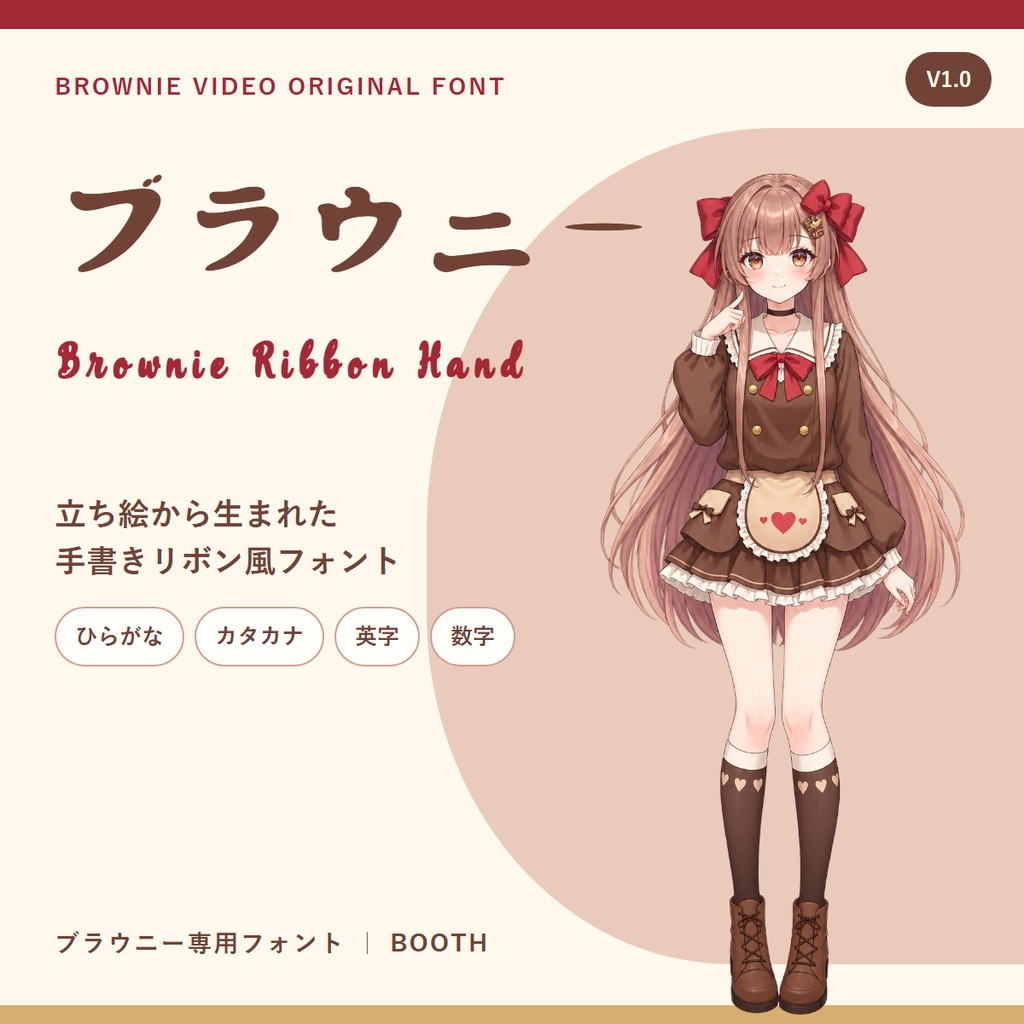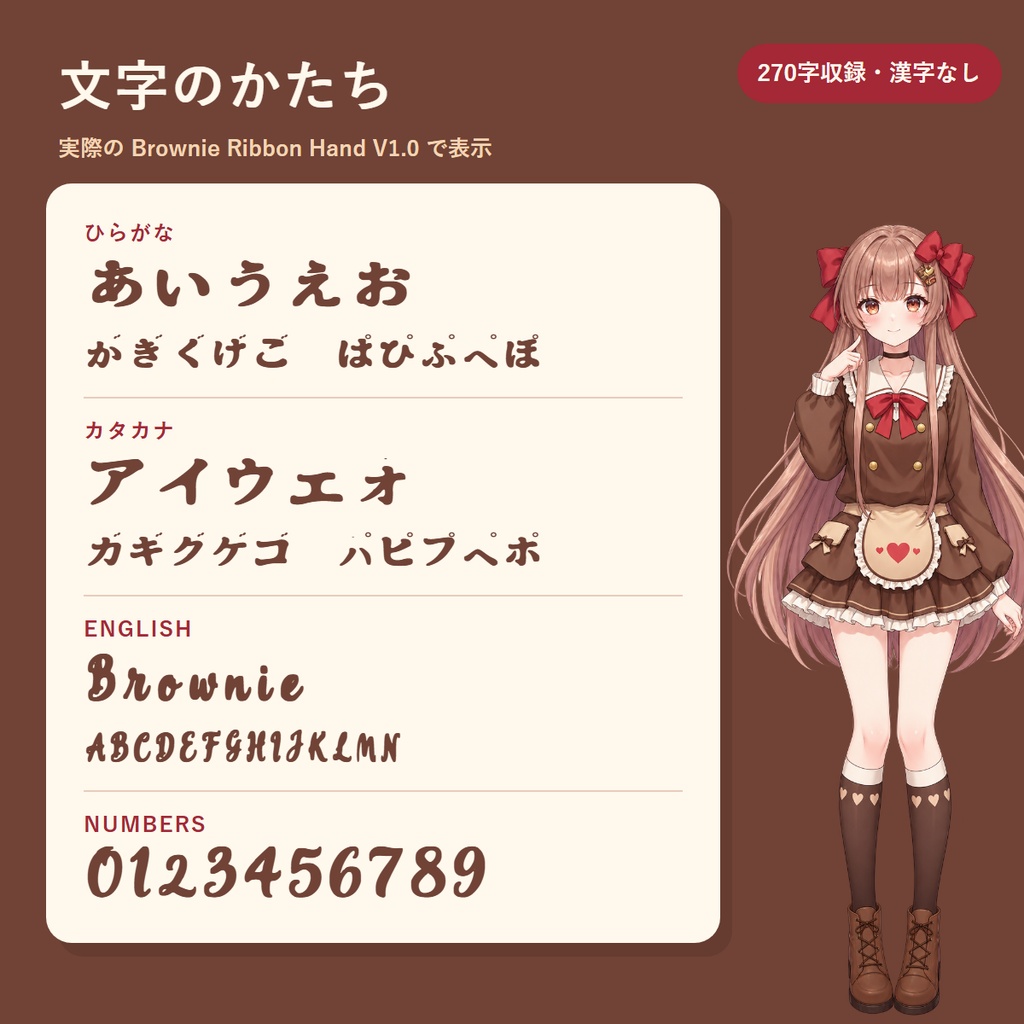
ブラウニーのイメージしたフォント
【商品紹介】 TITAN学園として登場するブラウニーの立ち絵にあるリボンと衣装の雰囲気をもとに制作した、手書き風のタイトル用フォント「Brownie Ribbon Hand V1.0」です。動画のタイトル、サムネイル、配信画面、ロゴ、印刷物などの文字表現に使えます。 【収録文字】 ひらがな、カタカナ、英大文字・小文字、数字、基本的な句読点と記号の計270字。漢字は収録していません。大きめの見出し向けです。短い字幕では48px以上を目安に、実際の画面で読みやすさを確認してください。 【価格と利用】 同じフォントデータを、購入者の区分に応じて販売します。適切な区分で購入すれば、商用利用、自作作品の収益化、完成作品の販売・納品、R18作品での使用ができます。クレジット表記は任意です。 ・一般個人:500円。受託制作や事業利用をしない方。自作作品の収益化は可能です。 ・個人事業・中小企業:3,000円。 ・大企業:20,000円。中小企業者の範囲に入らない法人が対象です。 【主な禁止事項】 ・フォントファイルの再配布・転売、購入権の転売、差別的な内容への使用 ・ブラウニーに悪意ある印象を与える使用、作り話による不安煽り、金融・政治、宗教等の対立煽り ・独自性の乏しい拡散目的の量産動画への使用は禁止です。 ・完成作品は販売でき、販売先も制限しません。差別を批判・解説する作品は禁止対象ではありません。 【ダウンロード内容】 Brownie_Ribbon_Hand_V1.0.ttf LICENSE_ja.txt 商品画像に使ったブラウニーの立ち絵、既存ロゴ、制作原稿はZIPに含みません。本商品はフォントの使用権であり、キャラクター画像の使用権は含みません。 この商品はAIで作成したものです。